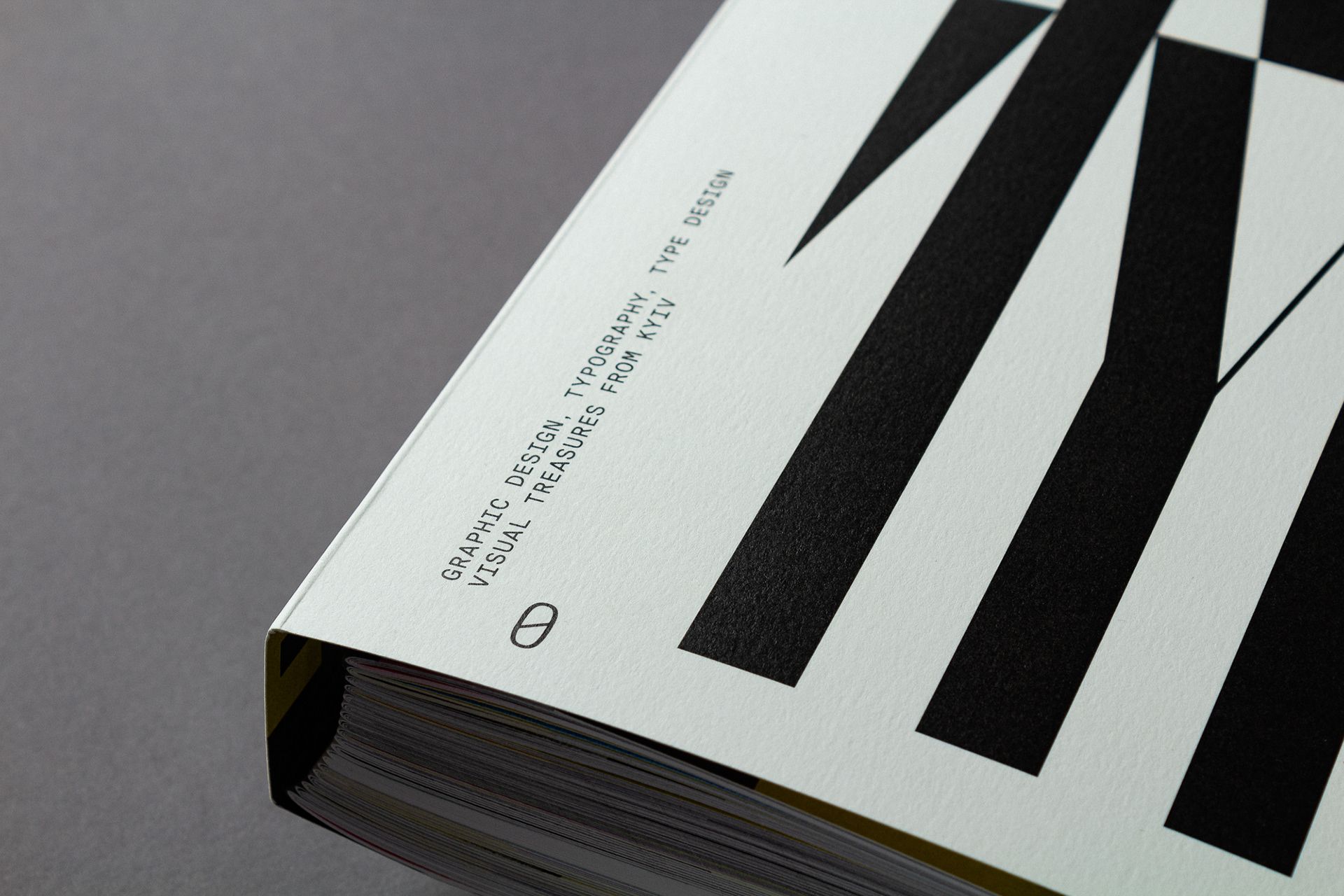
Sebastian Schubmehl diplomamunkája, a KYIV TYPE hiánypótló módon közelíti meg és mutatja be az ukrán főváros, Kijev designszcénáját. Gyönyörű, nagyvonalú kiadvány, mely intim betekintést enged a város életébe, bemutatva annak lakóit és egy különleges designpublikációt.
A projekt során a tervező végig szem előtt tartotta azt, hogy előzetes ismeretekkel nem rendelkező, a témában abszolút laikus olvasók is élvezettel forgathassák a könyvet.
A kötet vizuális megjelenésében a német tervezőgrafikus kijevi tartózkodása alatt szerzett élményei és benyomásai öltenek testet. Képeslapok, printek, poszterek, feliratok: tipográfiai és designtartalmakon, valamint a szerző saját fotóin keresztül elevenedik meg a mai Kijev arca.
Nem utolsósorban pedig szakmai nyelven, értő érzékenységgel közelíti meg és vizsgálja az ukrán fővárosban és annak tágabb környezetében megjelenő tipográfia, betűtervezés és design közti összefüggéseket.